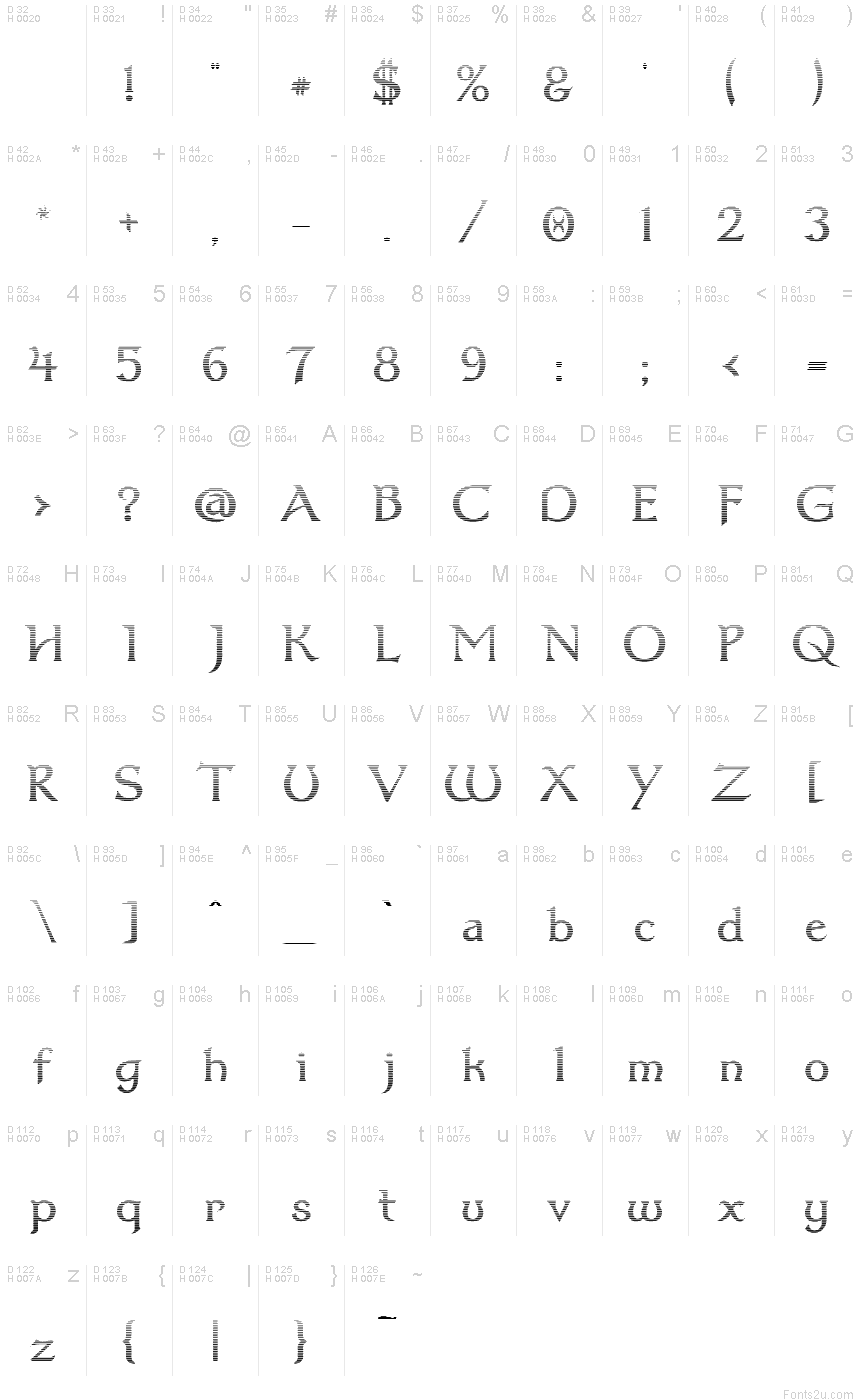
Dumbledor 1 Cut Down
Dumbledor 1 Cut Down od GeM/FF to bezpłatny, ozdobny krój szeryfowy o ciętej, pasiastej teksturze, która nadaje literom migotliwy, plakatowy charakter. Klasyczna szeryfowa sylwetka zapewnia czytelność, ale powtarzalne poziome nacięcia dodają krojowi teatralnego i lekko zużytego wyglądu, zachowując przy tym strukturę wystarczającą do wyeksponowania w dużych nagłówkach.
Dumbledor 1 Cut Down sprawdza się najlepiej tam, gdzie klimat jest ważniejszy niż długi tekst: na okładkach książek, plakatach fantasy, ulotkach wydarzeń, tytułach gier, gadżetach, nagłówkach rozdziałów i w brandingu tematycznym. Ten bezpłatny font ma dramatyczny rytm, który lubi duże rozmiary i dobrze komponuje się z prostym krojem szeryfowym lub neutralnym bezszeryfowym w tekście uzupełniającym.